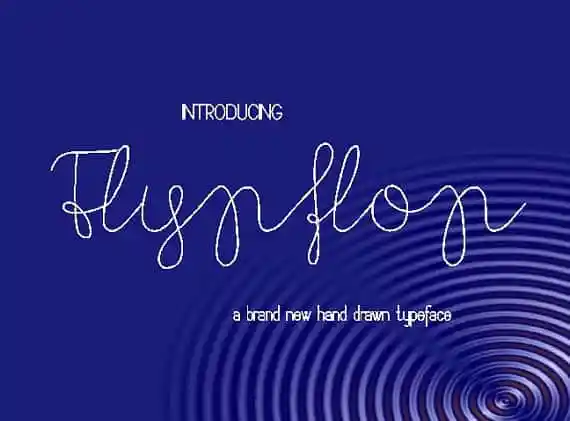
Flypflop Font
Aqui está uma descrição enxuta e envolvente para a página de download da font ‘Flypflop Font’, adequada à categoria de Fonts Manuscritas: O Flypflop é uma fonte manuscrita encantadora, perfeita para quem busca um touch elegante em projetos pessoais ou profissionais. Crie texturas interessantes com seu traçado suave e variável, ideal para headlines, textos de marca e designs gráficos delicados. Criada por Eva Barabasne Olasz, a fonte Flypflop oferece um estilo autêntico e único que remete à arte do desenho livre. Se você está procurando uma opção diferenciada para trabalhos manuscritos ou textos com efeitos especiais, o Flypflop é uma escolha ótima. O download inclui a versão demo gratuita, perfeita para experimentar as características únicas desta fonte. Para uso comercial, adquira a versão completa que vem com alinhamento automático (kerning), caracteres complementares e símbolos monetários para um maior alcance no design. Visite https://www.etsy.com/shop/DigitalTypefaceS para mais informações sobre os detalhes da versão completa e o contrato de licenciamento comercial. O Flypflop é uma fonte manuscrita perfeita para qualquer criador que busque personalidade em seu trabalho visual.
Designer: Eva Barabasne Olasz